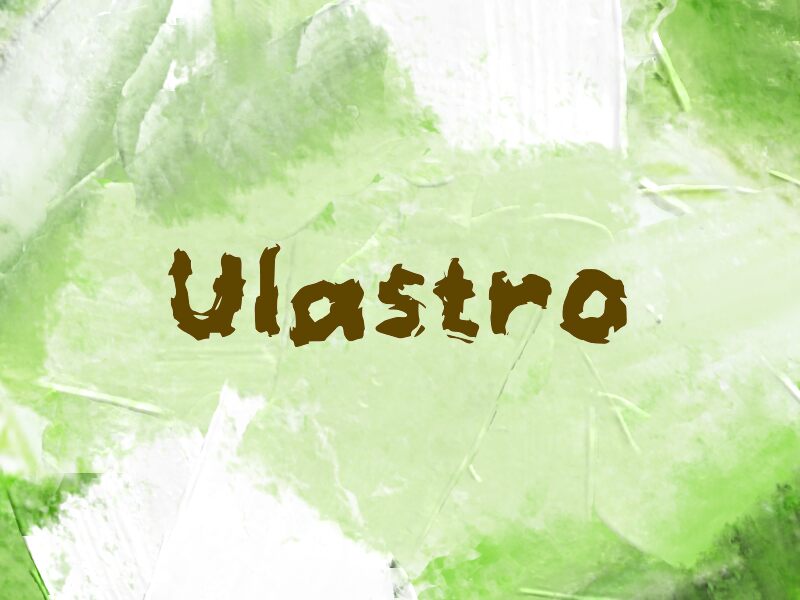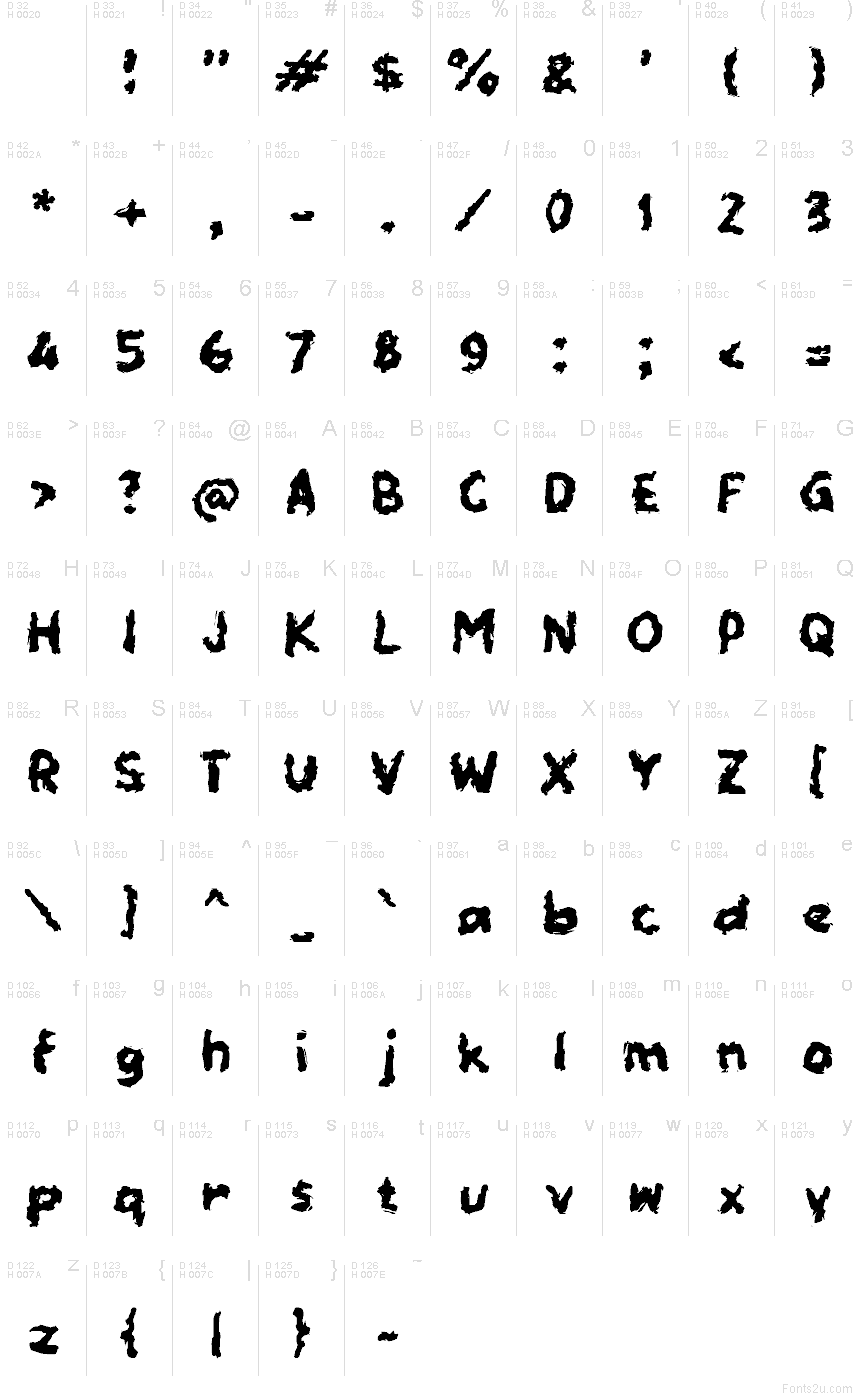
Ulastro par Wep est une police display gratuite au style « trash », avec une silhouette déchirée à la main qui semble brute et sauvage. Les lettres donnent l'impression d'avoir été taillées dans des formes lourdes, avec des bords dentelés, des encoches franches et des contours irréguliers qui rendent la texture physique et percutante plutôt que propre.
Elle est idéale pour les affiches, les graphismes de musique underground, les couvertures de fanzines, les titres de films d'horreur et le branding streetwear où le lettrage doit être écorché et immédiat. En tant que police gratuite, Ulastro convient parfaitement aux titres courts, aux cartons de présentation et aux essais de logos bruts, car ces bords déchiquetés font tout le travail, même sur quelques lettres.